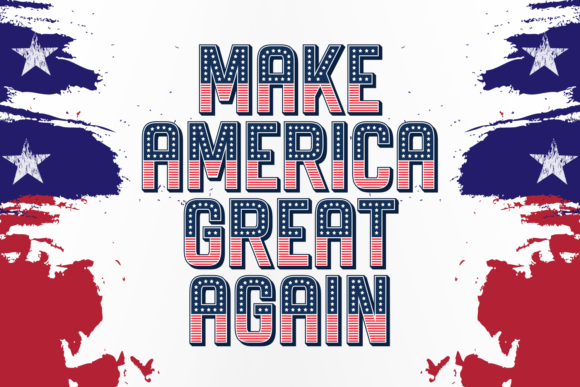
USA Cheer Font – الخط المثالي لتصاميمك الاحترافية!
أضف لمسة من الحماس والطاقة إلى تصاميمك مع USA Cheer Font، الخط المثالي للمشاريع التي تحتاج إلى طابع رياضي، حيوي، وجذاب. يتميز هذا الخط بأسلوبه القوي والجريء، مما يجعله مثاليًا لاستخدامه في تصميم الشعارات، الملابس الرياضية، الملصقات، وسائل التواصل الاجتماعي، وأكثر!
???? مميزات الخط:
✔️ تصميم احترافي مستوحى من الروح الرياضية الأمريكية
✔️ مناسب للعناوين الجريئة والمحتوى الإبداعي
أطلق العنان لإبداعك وأضف لمسة مميزة إلى تصاميمك مع USA Cheer Font! ????????